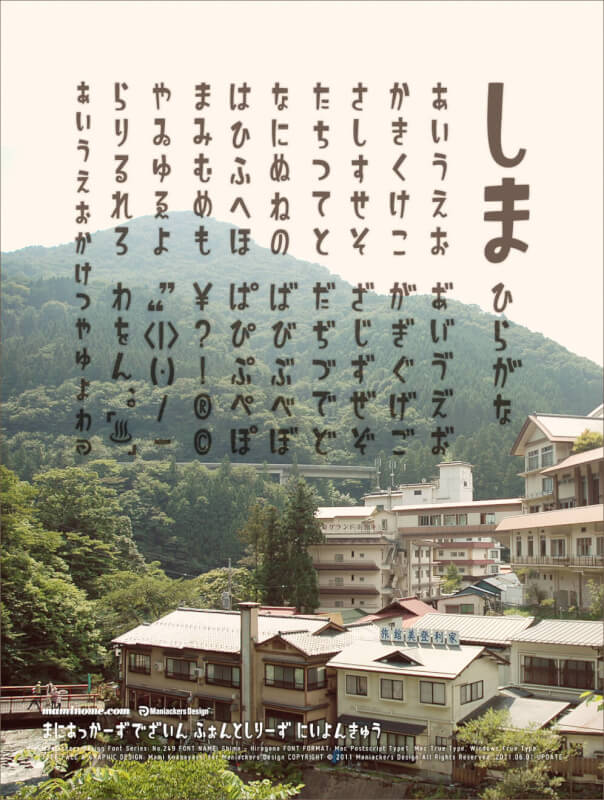
にくまるフォントは、ふっくらした太めの字形とやさしいシルエットが特徴で、子ども向け商品やポップな広告に最適です。親しみやすい雰囲気を演出したいロゴや見出しにもぴったりですよ。
いかほは、丸みを帯びた太めのシルエットが特徴で、親しみやすさと遊び心を演出します。子ども向けイベントのチラシや遊園地のデザインにぴったりです。
アンニャントロマンは、ハサミで切り取ったような不規則なエッジと太めのデザインが特徴で、ポスターやイベント告知にぴったりです。ユーモラスで躍動的な印象を与えます。
玉ねぎ楷書「激」は、筆で力強く書いたような太めの線と墨文字の風合いが特徴です。丸みと角ばりが共存し、柔らかさと力強さが絶妙に混ざっています。和風イベントのチラシや飲食店のメニューにぴったりですよ。
FZゴンタかなは、極太で角ばったデザインが特徴で、下重心のシルエットが安定感を演出します。インパクトを重視したタイトルやロゴ、バラエティ番組の字幕、ポップ広告の見出しに最適です。
コーポレート・ロゴ(ラウンド)は、角に丸みをもたせた太めの線が特徴で、優しい印象を与えます。商品ロゴや企業ロゴ、タイトルや見出しに最適で、親しみやすさと安心感を伝える広告やチラシにもおすすめです。
チェックポイント★リベンジは、極太で無骨なラインと角ばった直線が特徴のフォントです。スポーツチームやアクション系コンテンツのロゴ、ゲームのタイトル画面に最適です。
めもわーるは、丸みのある極太デザインで可愛らしさと存在感を両立し、遊び心のあるゆるい形が特徴です。子ども向け商品やポップなイベントの告知にぴったりで、可愛さを演出したいロゴにも最適です。
昔々ふぉんとは、ぽってりした丸みとゆるやかな線の揺らぎが特徴で、親しみやすくレトロな味わいがあります。子ども向けイベントやレトロ風カフェのロゴにぴったりで、あたたかい雰囲気を演出しますよ。
えるまーフォントは、手書き風の柔らかい線と丸みのある形状が特徴で、自然な書き味を感じさせます。子ども向けの絵本や教材、カフェのメニュー、親しみやすいウェブサイトやチラシにぴったりです。
851チカラヅヨクは、筆ペン風の力強い筆致とエッジの効いたデザインが特徴です。スポーツイベントやライブ告知、ストリート系ファッションの見出しに最適です。
じゆうちょうフォントは、太めで丸みのあるポップな字形が特徴で、親しみやすさと読みやすさを兼ね備えています。子ども向け教材やカフェのロゴ、SNS投稿にもぴったりです。
ニコ角フォントは、角ばったモダンなデザインにやや丸みを加えた、視認性の高いフォントです。WEBやアプリのUI、YouTube字幕などに最適で、デジタル広告にもぴったりです。
フィバ字は、大胆なジグザグ形状と個性的なシルエットが特徴のフォントです。ポップで動きのあるレイアウトが、子ども向けイベントやバラエティ番組のタイトルにぴったりです。
Nikkyou Sansは、極太で角ばったデザインが特徴のフォントです。直線中心のスッキリした形で、漢字も英語も統一感があります。イベント告知やゲームのロゴ、元気な印象を伝えたいポスターに最適です。
ニコモジ+(プラス)は、角の丸いモダンなデザインと太めの線幅が特徴で、親しみやすさと近未来感を演出します。ゲーム実況や配信サムネイル、ポップなバナーに最適です。
毛筆太文字は、太く勢いのある筆文字風デザインで、和風の商品ロゴや飲食店のメニューに最適です。自然な強弱と墨の濃淡が印象的で、イベントのタイトルにもぴったりです。
毛筆フォントは、細めで流れるような筆文字風のラインが特徴で、手書き感のある自然な抑揚が魅力です。和風のタイトルやメニュー表、季節の挨拶状などにぴったりです。
ちはや角は、ざっくりとした太めの輪郭と手作り感のある線が特徴で、力強さと親しみを両立しています。子ども向け教材や絵本の見出し、お店のPOP、イベントチラシ、動画のテロップなどに最適です。
しまひらがなは、素朴で温かみのある直線的な字形が特徴で、親しみやすさを演出します。子ども向けの絵本や教材、店舗のポップ、ナチュラル系の雑貨デザインにぴったりです。